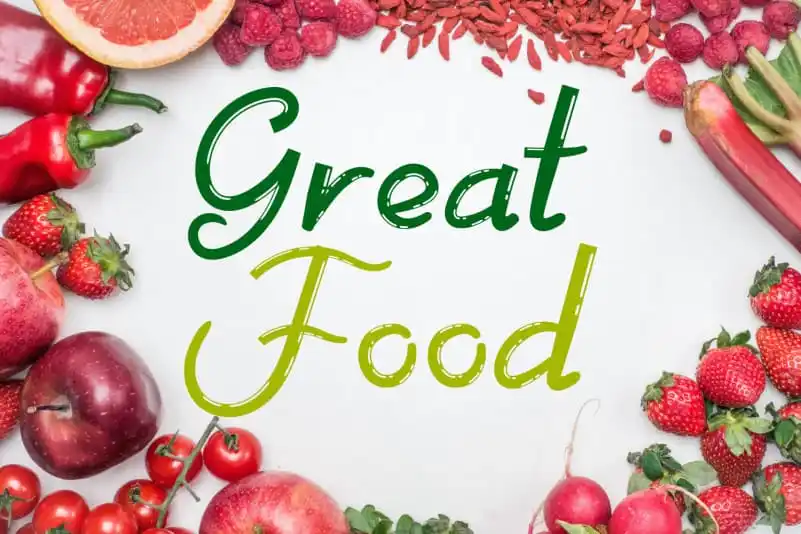
Great Food Script Font – Download Grátis
A Great Food Script Font é uma elegante tipografia escrita a mão que transmite delicadeza e fluidez ao mesmo tempo. Com caracteres belos e equilibrados, ela se adequa perfeitamente a um amplo espectro de designs. Este estilo de fonte irá transformar suas ideias mais criativas em uma arte vibrante e concreta. Para qualquer projeto que você esteja planejando, considere adicionar esta fonte Great Food Script para ver como ela recria sua visão com vida e graça. Essa é a fonte perfeita para aqueles projetos onde desejas expressar delicadeza através do texto.